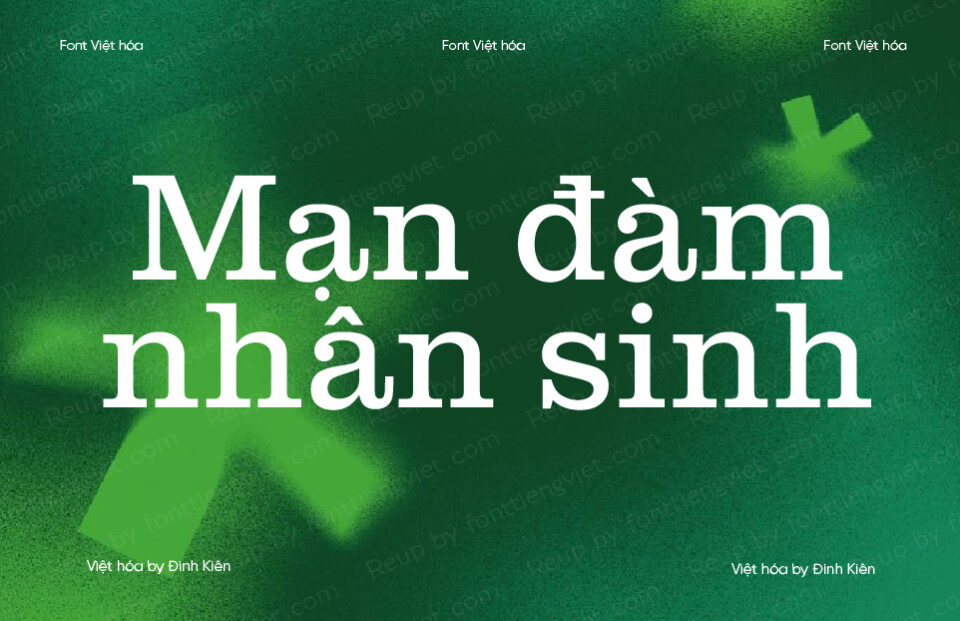
Trong thế giới thiết kế đồ họa rộng lớn, việc lựa chọn một Font Chữ phù hợp có vai trò cực kỳ quan trọng, quyết định đến tính thẩm mỹ và hiệu quả truyền đạt của tác phẩm. Đặc biệt, đối với các ấn phẩm tiếng Việt, nhu cầu về những bộ font chất lượng cao, được việt hóa đầy đủ là điều không thể thiếu. Nổi bật trong số đó là Font Việt hóa UTM Clarendon, một lựa chọn được nhiều nhà thiết kế ưa chuộng bởi sự kết hợp hoàn hảo giữa nét cổ điển và sự hiện đại, mang đến vẻ đẹp sang trọng, chuyên nghiệp cho mọi dự án. Bài viết này sẽ đi sâu khám phá về Font UTM Clarendon Việt hóa, từ lịch sử, đặc điểm nổi bật đến cách ứng dụng hiệu quả trong các lĩnh vực khác nhau, giúp bạn tận dụng tối đa tiềm năng của bộ font tuyệt vời này.
Font Việt hóa UTM Clarendon: Nguồn Gốc Và Đặc Điểm Nổi Bật
Font Clarendon ra đời vào năm 1845 bởi nhà thiết kế Robert Besley, đánh dấu một bước ngoặt quan trọng trong lịch sử typografi. Đây là một trong những kiểu chữ slab-serif đầu tiên, nổi tiếng với nét mạnh mẽ, dứt khoát và vẻ ngoài đầy uy quyền. Ban đầu, Clarendon được tạo ra với mục đích sử dụng trong in ấn tiêu đề sách, báo và các tài liệu chính thức, nơi cần sự rõ ràng và sức hút thị giác mạnh mẽ. Qua thời gian, nó đã trở thành một biểu tượng của sự đáng tin cậy và truyền thống. Tuy nhiên, để đáp ứng nhu cầu sử dụng trong ngôn ngữ tiếng Việt, việc việt hóa là cực kỳ cần thiết. Đó là lý do Font Việt hóa UTM Clarendon ra đời, do nhóm UTM Font thực hiện. Phiên bản UTM Clarendon Việt hóa không chỉ giữ nguyên được tinh thần và đặc trưng của bản gốc mà còn được bổ sung đầy đủ các ký tự tiếng Việt, dấu câu, giúp người dùng dễ dàng tạo ra các văn bản tiếng Việt mượt mà, chuyên nghiệp mà không gặp phải lỗi font hay hiển thị sai lệch.
Một trong những đặc điểm nổi bật nhất của Font Việt hóa UTM Clarendon chính là sự cân bằng tuyệt vời giữa các nét chữ. Các serif (chân chữ) vuông vắn, mạnh mẽ nhưng không quá thô cứng, tạo nên một sự ổn định và đáng tin cậy. Nét thanh và nét đậm được điều chỉnh một cách tinh tế, mang lại cảm giác hài hòa và dễ chịu khi đọc. Điều này khiến UTM Clarendon trở thành một lựa chọn lý tưởng cho cả tiêu đề lẫn nội dung chính. Hơn nữa, với phiên bản việt hóa, người dùng có thể tự tin sử dụng font này trong mọi ngữ cảnh, từ thiết kế logo, poster, brochure cho đến các tài liệu học thuật, website hay ứng dụng di động, mà không lo ngại về vấn đề tương thích tiếng Việt. Sự kết hợp giữa vẻ đẹp cổ điển và khả năng ứng dụng hiện đại đã giúp Font UTM Clarendon Việt hóa chiếm được cảm tình của đông đảo cộng đồng thiết kế.
Lợi Ích Khi Sử Dụng Font UTM Clarendon Việt Hóa Trong Học Tập Và Công Việc
Đối với học sinh, sinh viên và những người làm việc trong môi trường học thuật, việc sử dụng Font Việt hóa UTM Clarendon mang lại nhiều lợi ích đáng kể. Đầu tiên, với độ rõ ràng và dễ đọc cao, font này giúp các tài liệu học tập, báo cáo, luận văn trở nên chuyên nghiệp và dễ tiếp thu hơn. Các giáo viên cũng có thể sử dụng font này để tạo ra các đề thi, giáo trình hoặc bài giảng với bố cục mạch lạc, giúp học sinh dễ dàng tập trung vào nội dung chính. Đặc biệt, trong bối cảnh các kỳ thi tốt nghiệp trung học phổ thông hay các bài kiểm tra quan trọng, việc trình bày tài liệu một cách rõ ràng, dễ nhìn có thể ảnh hưởng tích cực đến tâm lý của người đọc và người chấm.
Trong lĩnh vực thiết kế và truyền thông, Font UTM Clarendon Việt hóa là một công cụ mạnh mẽ để xây dựng thương hiệu và tạo ấn tượng thị giác. Các doanh nghiệp có thể sử dụng font này trong logo, bao bì sản phẩm, quảng cáo để truyền tải thông điệp về sự bền vững, đáng tin cậy và có giá trị. Sự kết hợp giữa nét cổ điển và hiện đại của Clarendon giúp thương hiệu trở nên độc đáo và nổi bật giữa hàng ngàn đối thủ cạnh tranh. Đối với các nhà thiết kế web, việc áp dụng Font Việt hóa UTM Clarendon vào giao diện người dùng có thể cải thiện trải nghiệm đọc, giúp website trở nên thu hút và chuyên nghiệp hơn. Đây cũng là một lựa chọn tuyệt vời cho các ấn phẩm in ấn như tạp chí, sách, báo, nơi yêu cầu cao về tính thẩm mỹ và khả năng đọc.
Tổng kết lại, Font Việt hóa UTM Clarendon là một lựa chọn tuyệt vời cho bất kỳ ai đang tìm kiếm một bộ Font Chữ mang đậm phong cách cổ điển nhưng vẫn giữ được nét hiện đại và chuyên nghiệp. Với khả năng việt hóa hoàn chỉnh, nó không chỉ đảm bảo tính thẩm mỹ mà còn tối ưu hóa trải nghiệm đọc cho người dùng tiếng Việt. Dù bạn là học sinh, sinh viên đang chuẩn bị tài liệu, giáo viên thiết kế bài giảng, hay một nhà thiết kế đồ họa chuyên nghiệp, Font UTM Clarendon Việt hóa chắc chắn sẽ là một công cụ đắc lực, giúp nâng tầm các tác phẩm của bạn. Hãy trải nghiệm và cảm nhận sự khác biệt mà font chữ này mang lại cho các dự án của bạn ngay hôm nay.